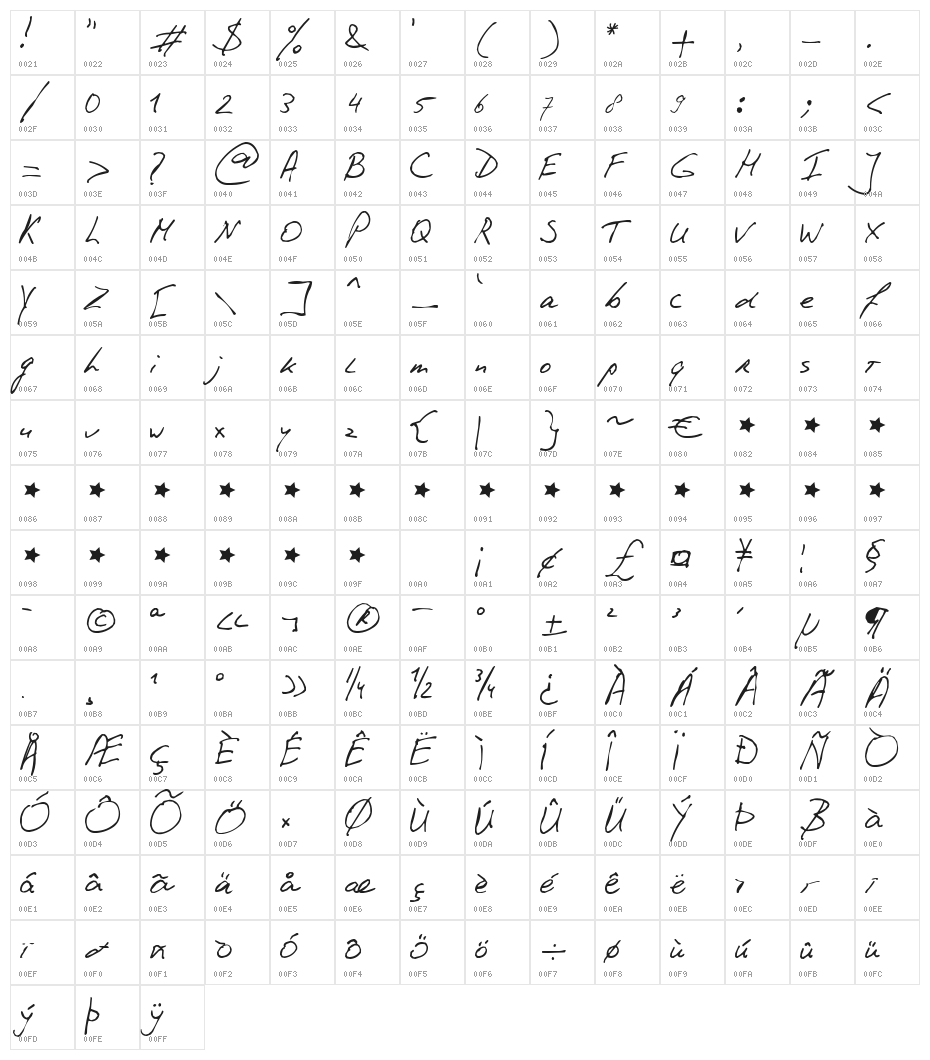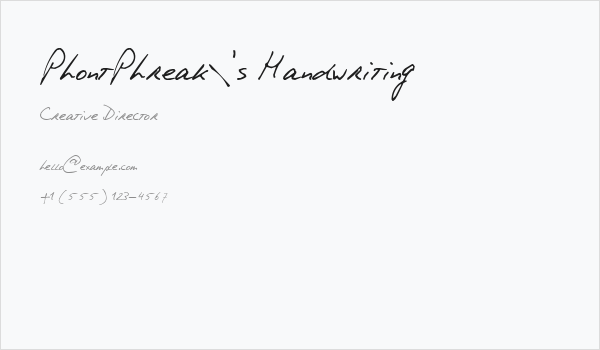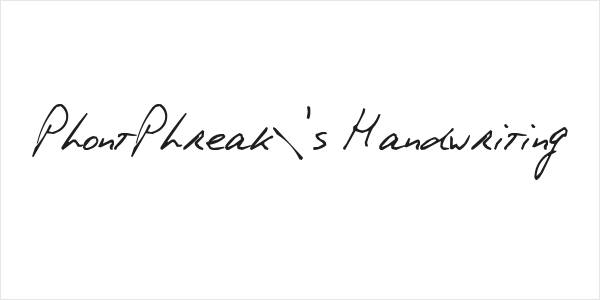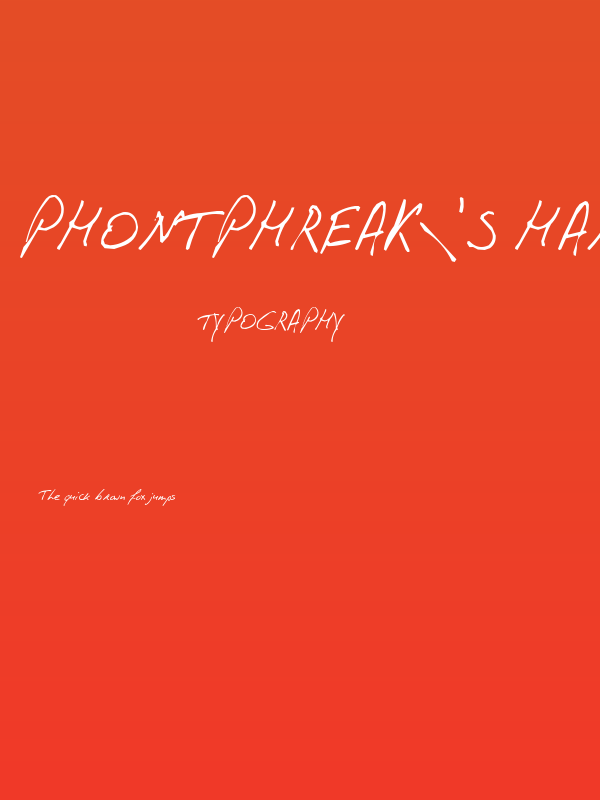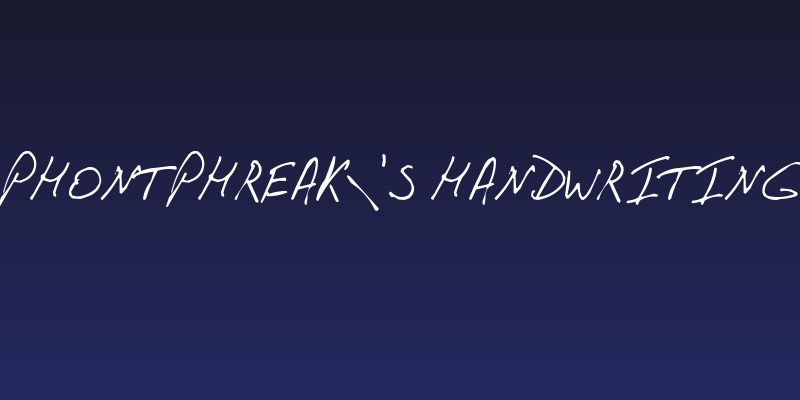
PhontPhreak's Handwriting Font
✎ Handwritten
| 分类 | Handwritten |
| 整体风格 | Casual, Informal |
| 使用场景 | Creative projects, Personal notes, Informal branding |
| 推荐项目 | Ideal for greeting cards, personal letters, creative invitations, and informal branding. |